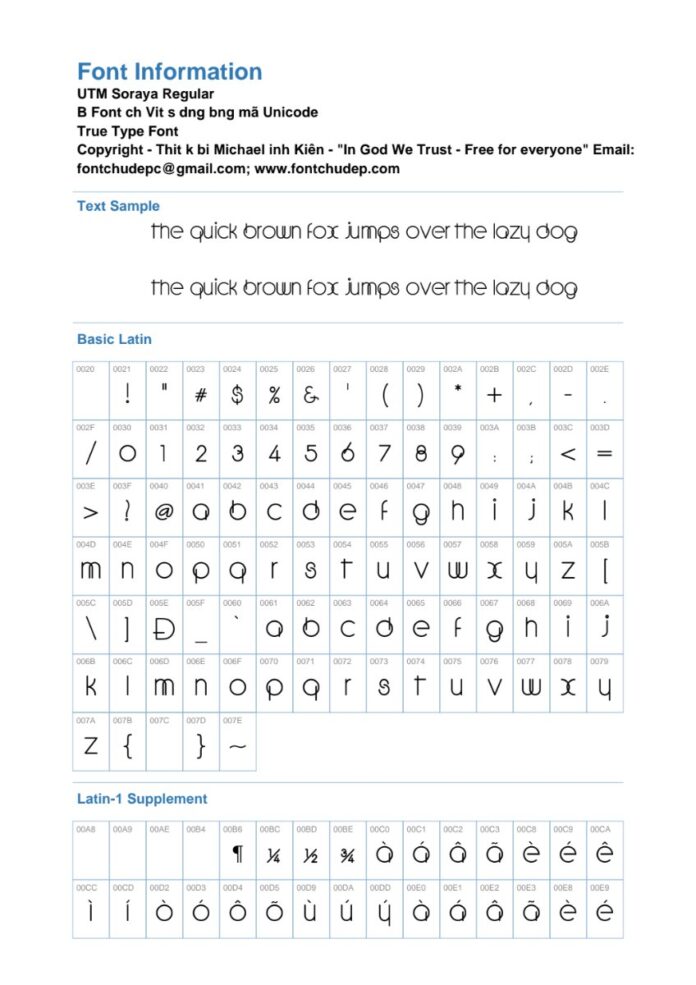
Font UTM Soraya là gì?
UTM Soraya là một kiểu chữ thuộc bộ sưu tập font UTM (UVN Vietnamese Fonts), nổi tiếng với việc hỗ trợ tiếng Việt đầy đủ và tối ưu. Font Soraya được thiết kế với phong cách hiện đại, mềm mại nhưng vẫn giữ được sự rõ ràng, dễ đọc. Đây là một font chữ không chân (sans-serif) với các đường nét bo tròn nhẹ nhàng, tạo cảm giác thân thiện và tinh tế. Sự kết hợp giữa nét truyền thống và hiện đại giúp UTM Soraya trở thành lựa chọn lý tưởng cho nhiều loại hình thiết kế khác nhau.
Đặc điểm nổi bật của Font UTM Soraya
• Hỗ trợ tiếng Việt đầy đủ: Một trong những ưu điểm lớn nhất của các font UTM nói chung và Soraya nói riêng là khả năng hỗ trợ tiếng Việt hoàn chỉnh, bao gồm tất cả các dấu và ký tự đặc biệt. Điều này giúp các nhà thiết kế Việt Nam dễ dàng tạo ra các ấn phẩm chuyên nghiệp mà không lo lỗi font.
• Thiết kế hiện đại, tinh tế: Với các đường nét mềm mại, bo tròn, UTM Soraya mang đến vẻ đẹp hiện đại, phù hợp với xu hướng thiết kế tối giản và thanh lịch.
• Tính ứng dụng cao: Font chữ này có thể được sử dụng trong nhiều ngữ cảnh khác nhau, từ thiết kế logo, tiêu đề, banner, poster cho đến nội dung website, sách báo và các ấn phẩm in ấn khác.
• Dễ đọc: Mặc dù có phong cách độc đáo, UTM Soraya vẫn đảm bảo tính dễ đọc, giúp truyền tải thông điệp một cách hiệu quả đến người xem.
Ứng dụng của Font UTM Soraya trong thiết kế
Với những đặc điểm nổi bật đã nêu, Font UTM Soraya có thể được ứng dụng rộng rãi trong nhiều lĩnh vực thiết kế:
Thiết kế thương hiệu và logo
Sự tinh tế và hiện đại của UTM Soraya làm cho nó trở thành một lựa chọn tuyệt vời cho việc thiết kế logo và nhận diện thương hiệu. Font chữ này có thể giúp các thương hiệu truyền tải sự chuyên nghiệp, thân thiện và đổi mới. Đặc biệt, với các thương hiệu hướng đến đối tượng trẻ, năng động, UTM Soraya sẽ là một điểm nhấn ấn tượng.
Thiết kế ấn phẩm quảng cáo
Từ banner, poster, flyer đến brochure, UTM Soraya đều có thể phát huy tối đa hiệu quả. Các tiêu đề sử dụng font này sẽ thu hút ánh nhìn, trong khi phần nội dung vẫn đảm bảo tính dễ đọc. Sự mềm mại của font cũng giúp làm dịu đi những thông điệp quảng cáo, tạo cảm giác dễ chịu cho người xem.
Thiết kế website và ứng dụng di động
Trong thiết kế giao diện người dùng (UI/UX), UTM Soraya có thể được sử dụng cho các tiêu đề, nút bấm hoặc thậm chí là nội dung chính. Font chữ này giúp tạo ra một giao diện thân thiện, hiện đại và dễ tương tác, nâng cao trải nghiệm người dùng.
Thiết kế sách báo và tạp chí
Với tính dễ đọc và vẻ đẹp thẩm mỹ, UTM Soraya cũng là một lựa chọn tốt cho việc thiết kế bìa sách, tiêu đề bài viết trong tạp chí hoặc các ấn phẩm in ấn khác. Nó giúp tạo ra một bố cục hài hòa và chuyên nghiệp.
Cách sử dụng Font UTM Soraya hiệu quả
Để tận dụng tối đa vẻ đẹp của Font UTM Soraya, bạn có thể tham khảo một số mẹo sau:
• Kết hợp với các font khác: UTM Soraya thường kết hợp tốt với các font serif cổ điển hoặc các font sans-serif đơn giản khác để tạo sự cân bằng và đa dạng trong thiết kế.
• Lưu ý về kích thước và khoảng cách: Điều chỉnh kích thước font và khoảng cách giữa các ký tự (kerning) và dòng (leading) để đảm bảo tính dễ đọc và thẩm mỹ.
• Sử dụng màu sắc phù hợp: Font UTM Soraya có thể phù hợp với nhiều bảng màu khác nhau, từ những màu sắc tươi sáng, trẻ trung đến những gam màu trầm, thanh lịch.